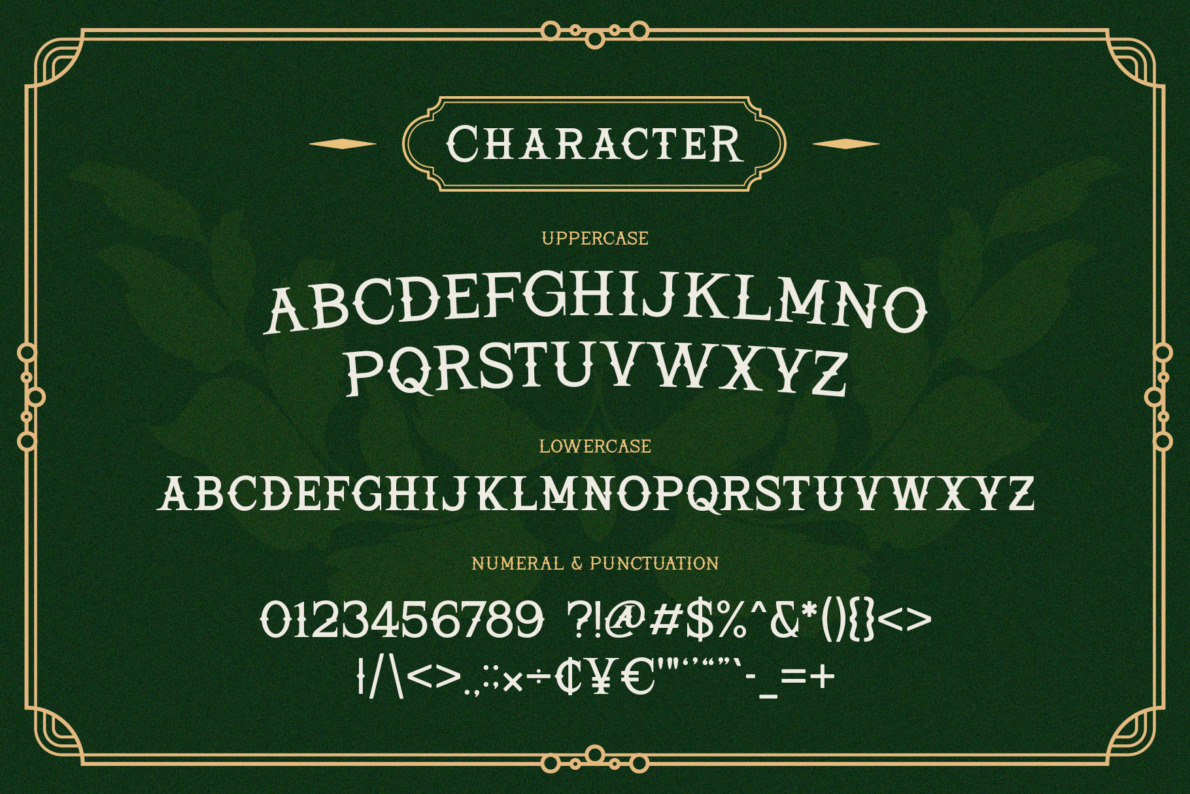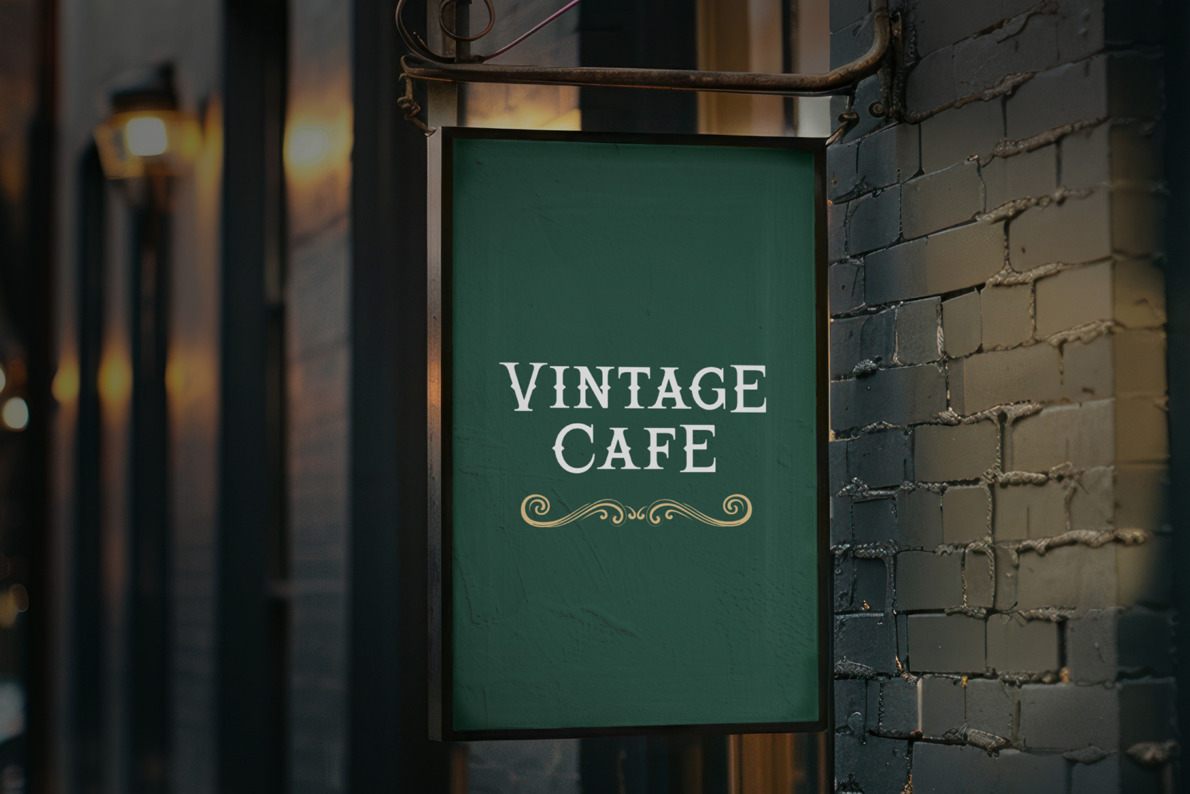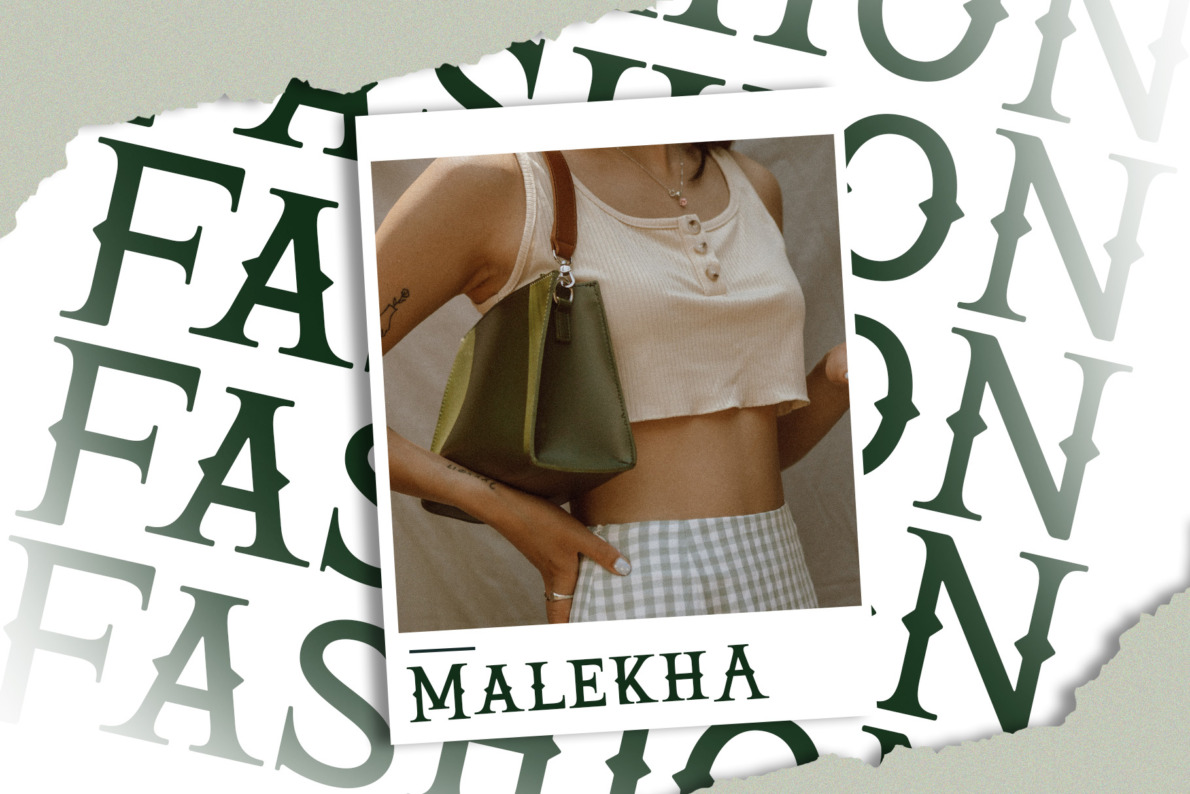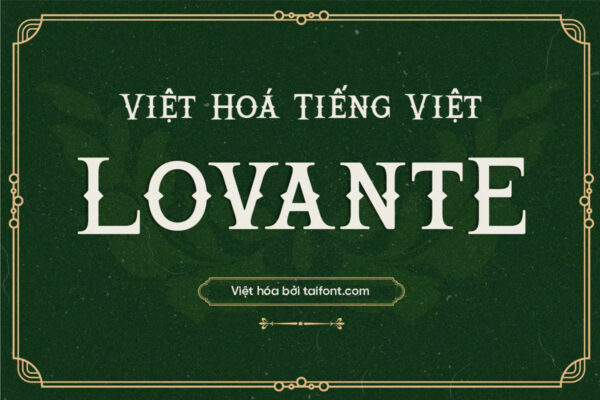
Giới thiệu về Font TF Lovante Việt hóa
TF Lovante Việt hóa là một font chữ nổi bật với thiết kế mang đậm phong cách vintage, cổ điển và đầy phong trần, lý tưởng để tái hiện vẻ đẹp xưa cũ, mạnh mẽ nhưng vẫn rất nghệ thuật. Font này toát lên sự vững chãi, uy nghi và một chút bụi bặm của thời gian, gợi nhớ về những bảng hiệu vẽ tay của các cửa tiệm truyền thống.
Với đặc điểm là phong thái hoài cổ và khả năng truyền tải sự tinh tế, Lovante là lựa chọn hoàn hảo cho các thiết kế muốn thể hiện sự đẳng cấp, sự bền vững và một chút lãng mạn của thời gian:
- Làm bảng hiệu tiệm cắt tóc (Barber Shop): Hoàn hảo để sử dụng cho các bảng hiệu của tiệm cắt tóc nam truyền thống, tiệm xăm, hoặc các cửa hàng mang phong cách retro. Font này giúp tạo không khí chân thực, “chất” và đầy tính nghệ thuật, thu hút những khách hàng yêu thích sự cổ điển.
- Các thiết kế kiểu cổ điển: Lý tưởng cho các dự án mang hơi hướng retro, chẳng hạn như poster phim cổ điển, bìa sách, nhãn mác sản phẩm hoặc các ấn phẩm kỷ niệm. Font này giúp tạo không khí chân thực và đầy hoài niệm mà không bị lỗi thời.
- Thiết kế nhận diện thương hiệu: Phù hợp cho các logo hoặc bộ nhận diện thương hiệu muốn truyền tải sự vững chãi, uy tín và một chút hoài cổ đầy phong cách.
Với TF Lovante Việt hóa, bạn có thể dễ dàng thổi hồn vintage, sự mạnh mẽ và cổ điển vào các thiết kế, tạo ra những sản phẩm không chỉ đẹp mắt mà còn đầy cảm xúc và chiều sâu.
Font Việt hóa TF Lovante – Phong chữ vintage